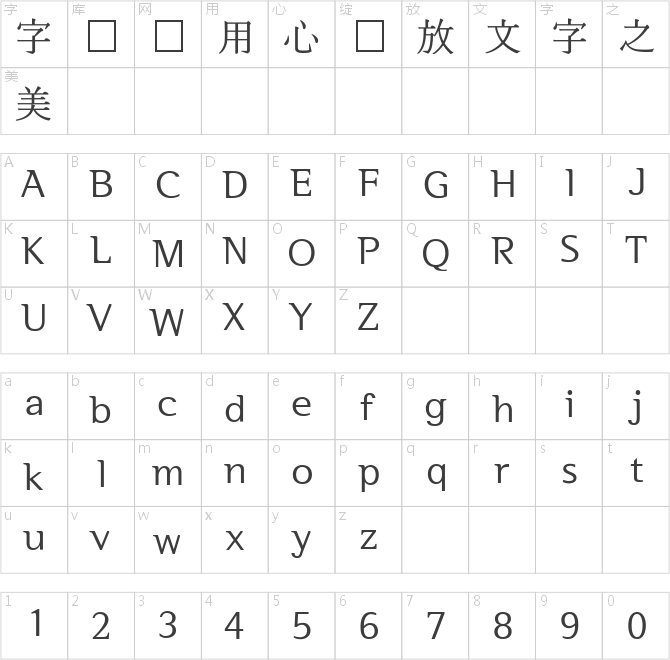
字体名称: 首爾漢江體
首爾漢江體
首爾漢江體字体下载SeoulHangang首尔汉江体
首尔市为广泛使用首尔的固有字体,提升城市认同性与品牌价值而开发出明体系列的4种首尔汉江体(Light、Medium、Bold、Extra Bold)和哥特体系列的4种首尔南山体(Light、Medium、Bold、Extra Bold)、1种竖写体等共9种首尔字体。
首尔字体中蕴含着强韧的儒生精神与端庄的余白美,从造型上展现了韩屋的开放和瓦片的曲线美。此外,首尔字体取名时采用首尔两大代表性资源“汉江”和“南山”,更能激发市民对韩民族固有美丽语言——韩文的文化自豪感。